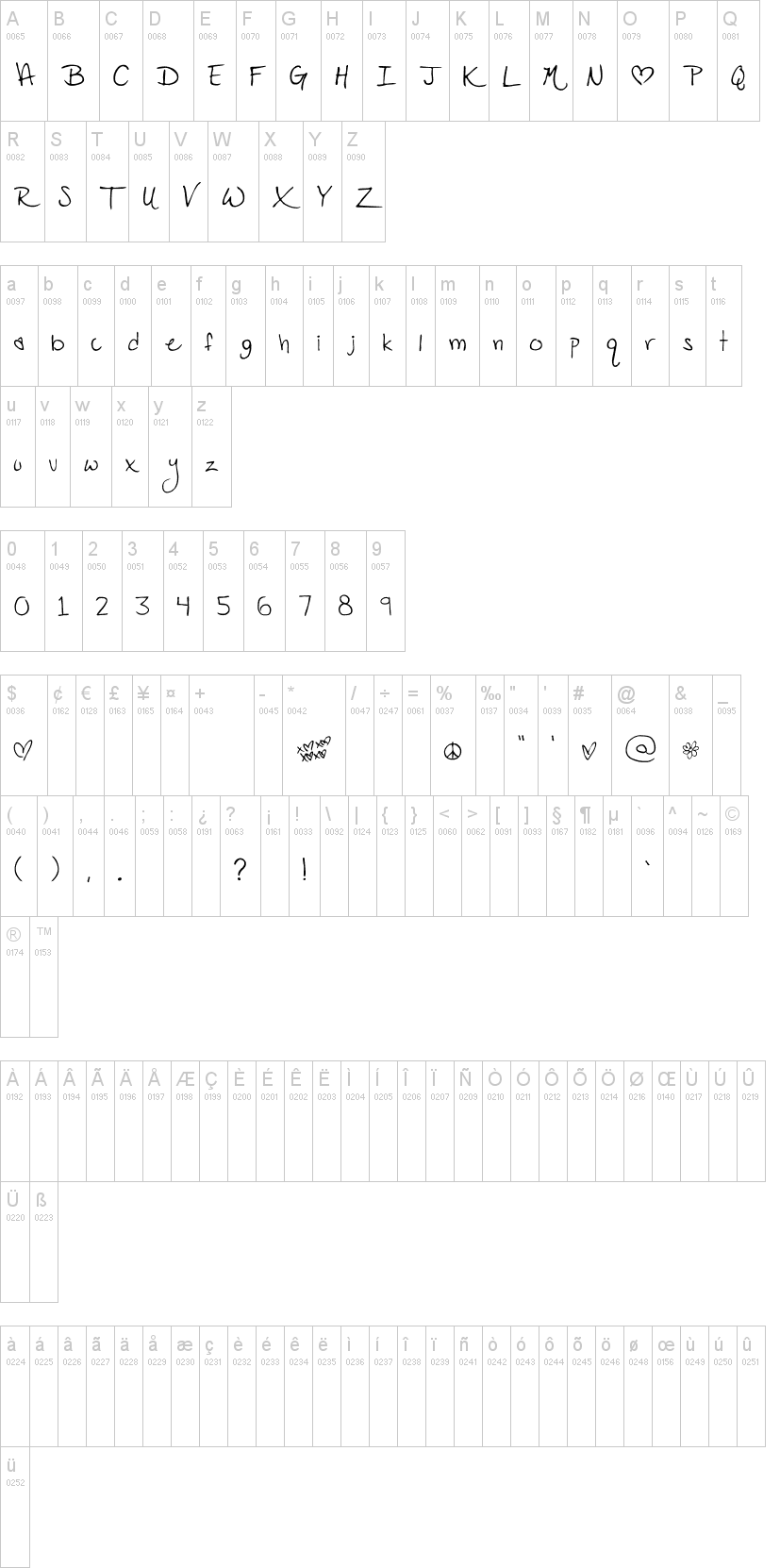
PopStar Autograph 字体是一种手写风格的字体,其设计灵感来自于流行音乐明星的签名。该字体的特点是每个字母都有一些装饰性的线条,这些线条使字母看起来非常流畅和动感。此外,PopStar Autograph 字体的字母大小不一,这增强了手写的感觉并增加了字体的个性化。 PopStar Autograph 字体适合用于海报、广告、书籍封面等需要吸引人眼球并打动人心的设计中。它的手写风格使得它显得非常亲切和自然,能够吸引读者的注意力并传达出温暖的情感。如果你正在寻找一种能够突显个性和个人风格的字体,PopStar Autograph 字体是一个不错的选择。内容介绍
PopStar Autograph是一款非常不错的手写艺术字体,具有很好的视觉感,适合于文化类的宣传设计、商业类品牌的广告和产品包装设计以及个性化文字排版等较多场景。